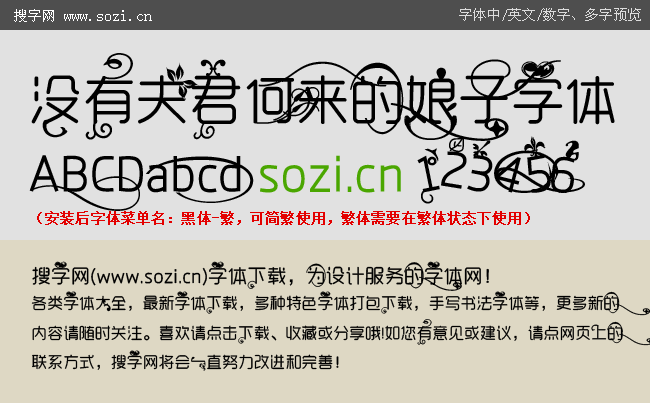
沒有夫君何來的娘子字體
搜字網(wǎng)給大家提供一款很有趣的手機(jī)中文字體下載。字體名字叫沒有夫君何來的娘子字體,這款手機(jī)字體是在造字工房悅黑體字體筆畫間插入了漂亮的卡通花紋圖案。趣味性實(shí)足,又保持了文字的識別度,特別適合喜歡手機(jī)字體個性一些的朋友在手機(jī)上安裝使用。